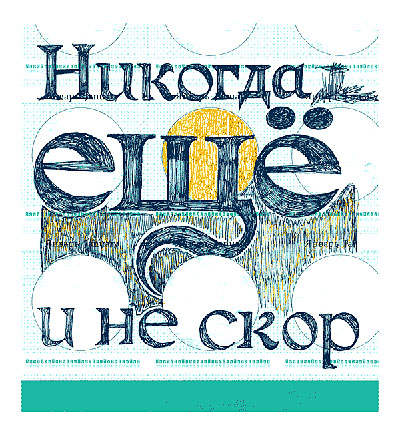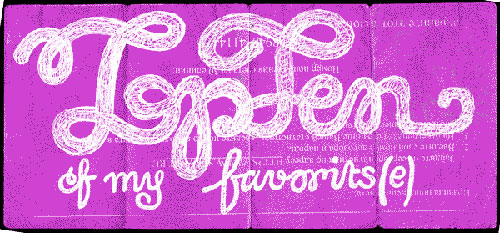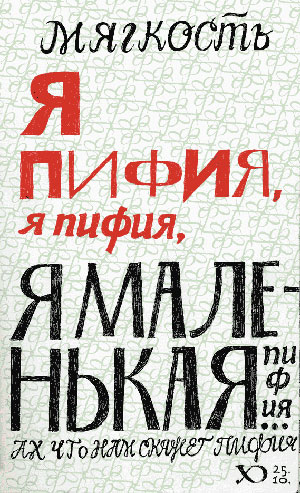
Unsere taegliche Schrift gib uns heuteDie wunderbare Webseite »Daily Type« der russischen
Schriftentwerfer Yury Ostromentsky, Dasha
Yarzhambek, Dmitry Jakovlev und Ilya
Ruderman beglückt Schriftenfreunde (fast) täglich mit einer
neuen typografischen Illustration. Seit über einem Jahr existiert die
anregende Galerie inzwischen, und jeden Tag beschenkt sie uns von neuem.
![]() Ilya Ruderman veröffentlichte diese Kugelschreiberskizze am 27. Oktober 2005 auf der Daily-Type-Seite (hier verkleinert). ![]() Auch diese sympathische Schreibschrift-Skizze stammt von Ilya Ruderman. ![]() Plakatidee von Yury Ostromentsky, veröffentlicht am 25. Oktober 2005. Herausgegeben: Mi - November 2, 2005 at 01:35 nachm. | |